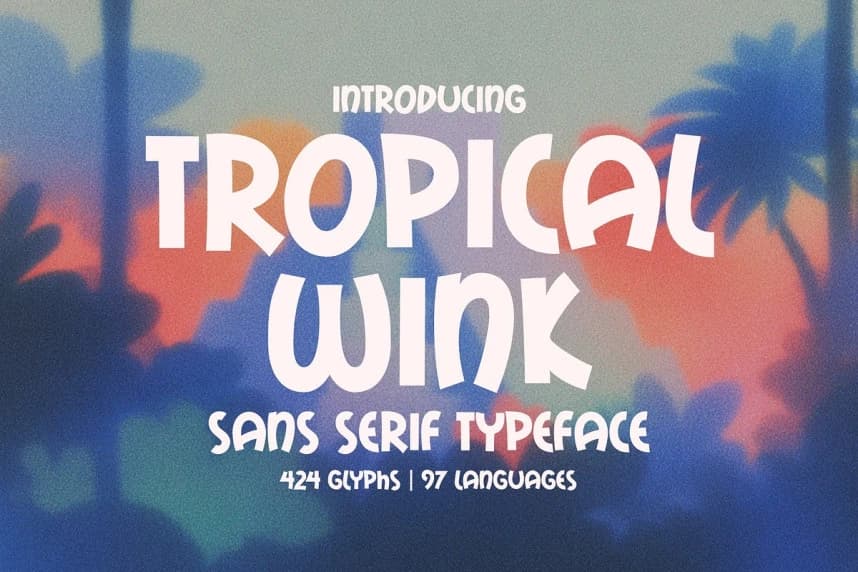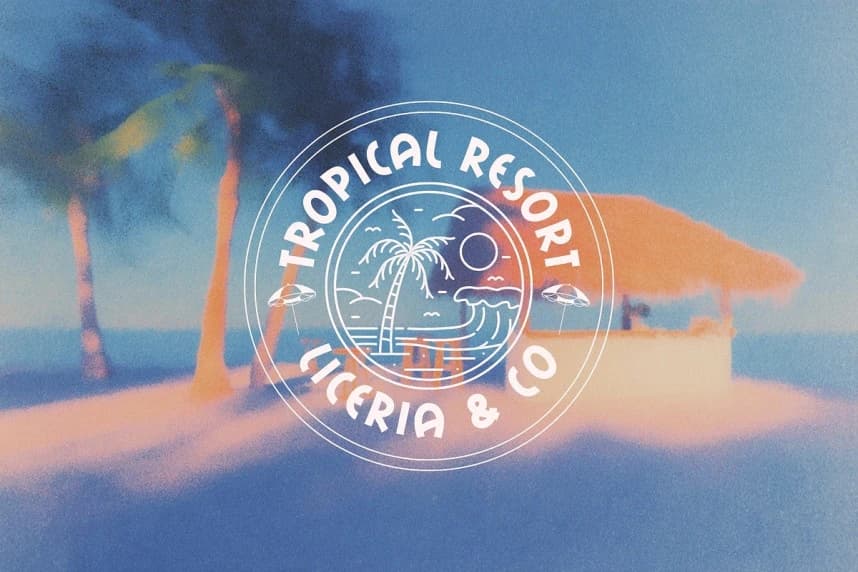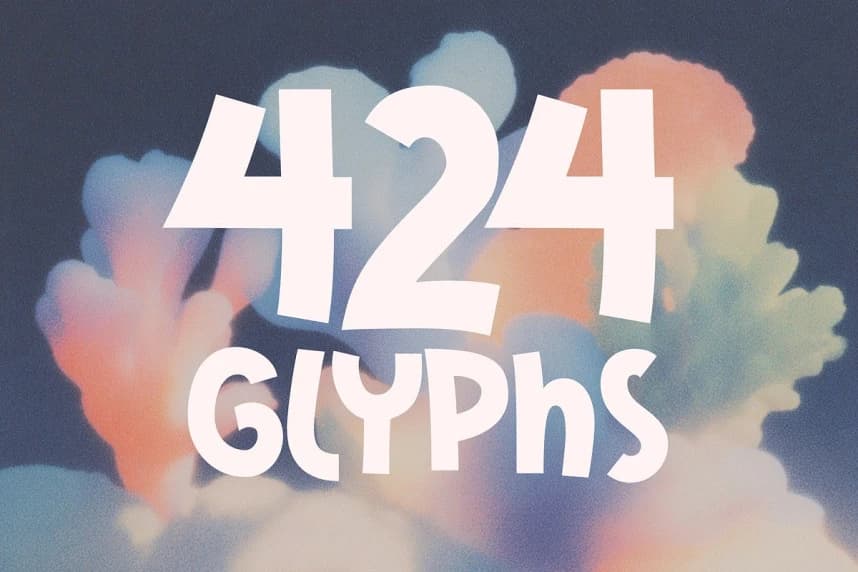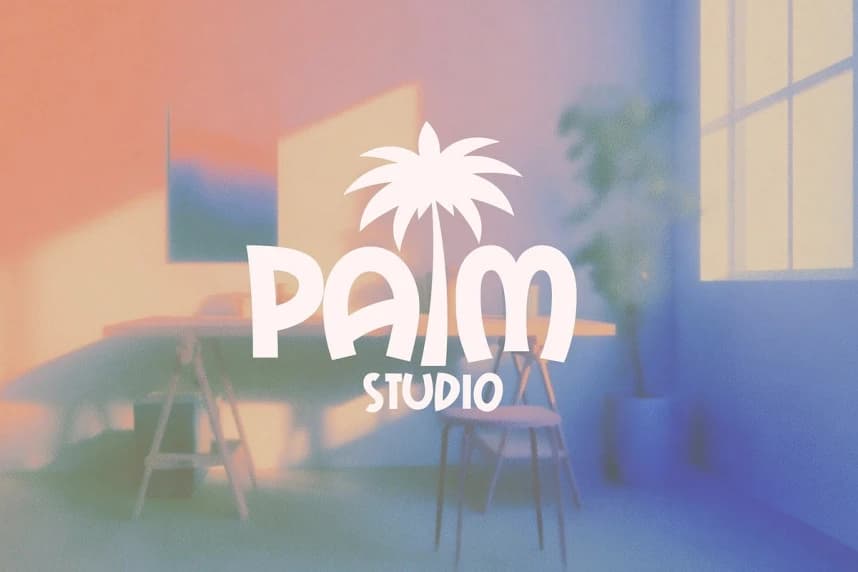
Tropical Wink Font
Tropical Wink Font, eğlence saçan kalın ve oyuncu bir sans serif yazı tipidir. Kalın, tuhaf harfleri ve neşeli kişiliğiyle bu yazı tipi, yaz mevsiminin kaygısız ruhunu yakalamak için mükemmeldir. İster hayali posterler tasarlıyor olun.
Tropical Wink Font, eğlenceli bir hava yayan kalın ve oyuncu bir sans serif yazı tipidir. Kalın, garip harfleri ve neşeli kişiliğiyle bu yazı tipi yaz mevsiminin kaygısız ruhunu yakalamak için mükemmeldir. İster hayal gücüyle dolu afişler tasarlıyor olun.
Tropical Wink
Tropical Wink Regular